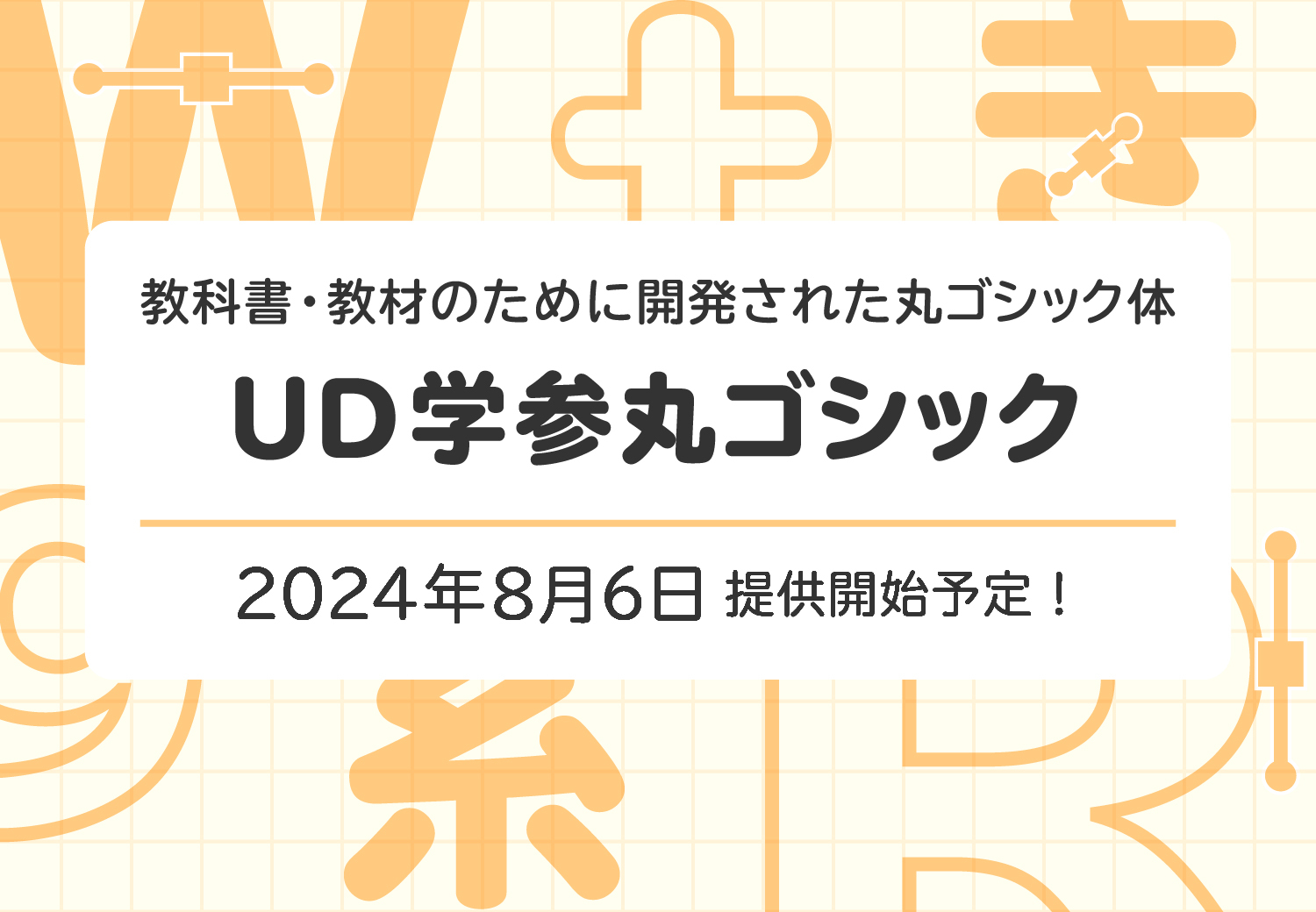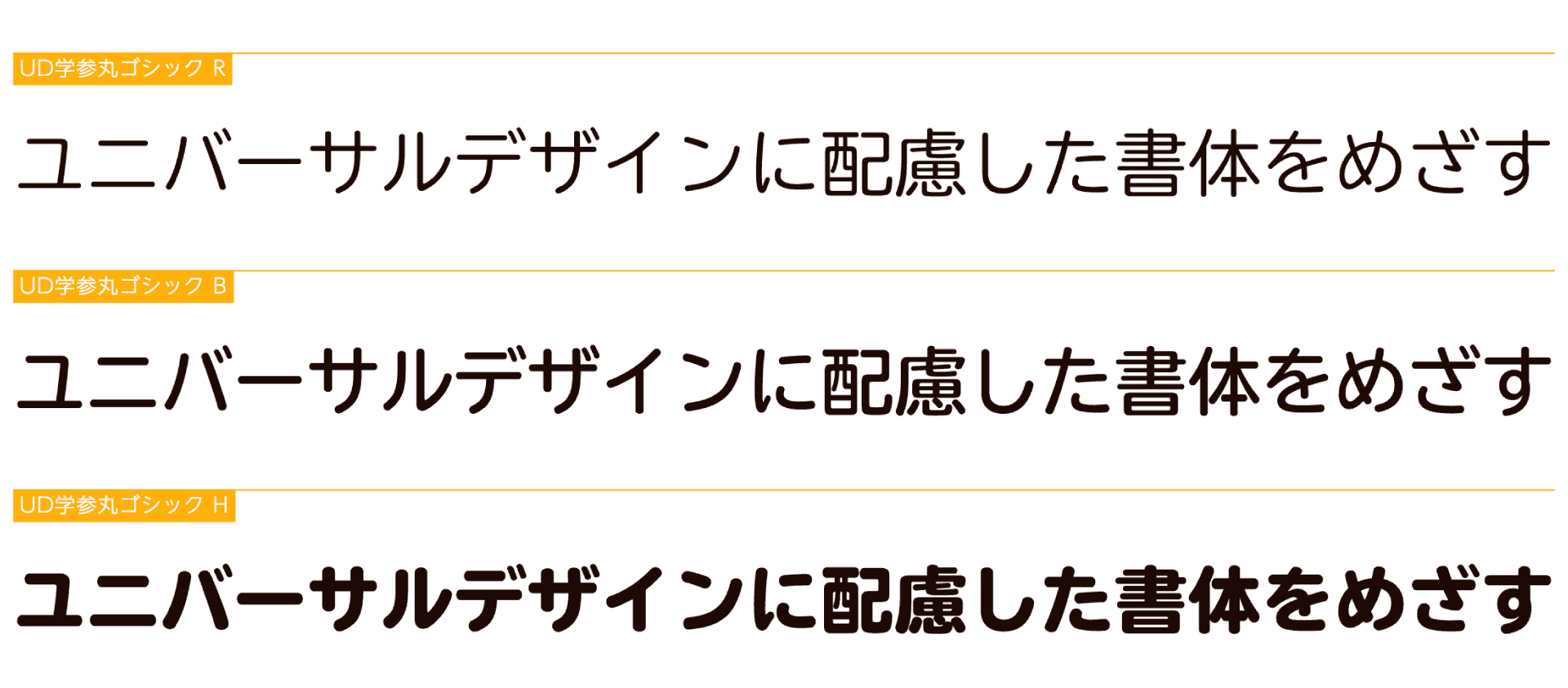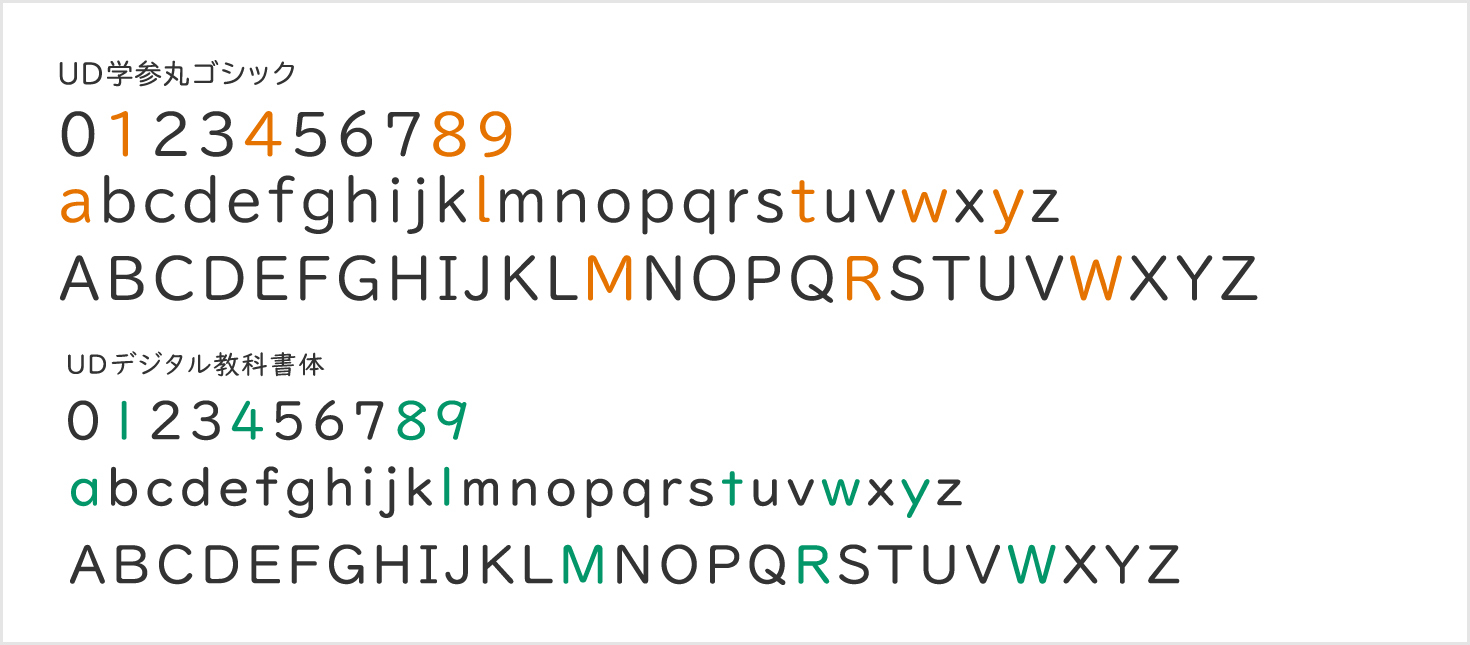
モリサワ より多くの方に読みやすく学習を支援する新書体「UD学参丸ゴシック」を8月6日提供開始
「UD学参丸ゴシック」は、教科書・教材のために開発された丸ゴシック体です。全ての和文の文字が文部科学省の学習指導要領の字形に準拠(学参化)しているため、「UDデジタル教科書体」と並んで、読み書きに困難さのある児童・生徒を含む多くの子どもたちの学習を支援する書体です。子どもたちの発達段階や使用目的などに合わせて、「BIZ UDゴシック」「UDデジタル教科書体」など他のUDフォントと併用したり、使い分けていただくことが可能です。
「UD学参丸ゴシック」の漢字やかなは、ひと文字ひと文字が大きく見えるように作られており、お年寄りやロービジョンの方の読み間違いが少なくなるよう、細かな工夫が施されています。ロービジョンの方を対象とした検証でも評価が高いフォントです。
英数字は、ロービジョンの方へのヒアリングを踏まえ、読み間違えにくいことに焦点を当てた丸ゴシックの形状が優先されています。学校で習う形状とは異なりますが、「1」と「l(小文字エル)」や、「a」と「o」、「W」と「VV」などの読み間違いを減らす工夫が施されています。グラフや表組みの数字表記などにも適しています。
福岡教育大学での学生約273名を対象としたアンケート調査では、複数の書体を比較した結果、4割以上の学生が「UD学参丸ゴシック」を最も英数字の形がはっきりわかる書体と回答しました。